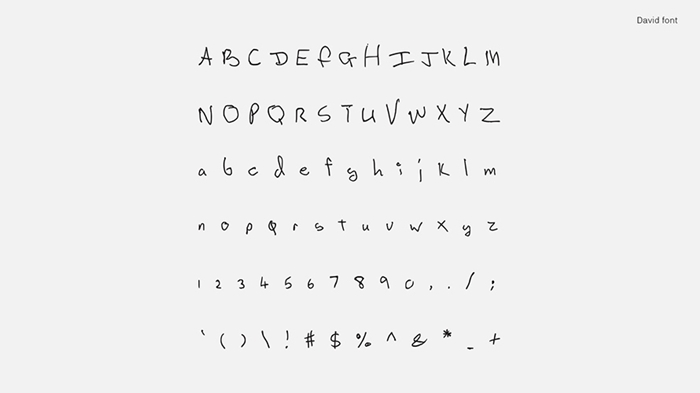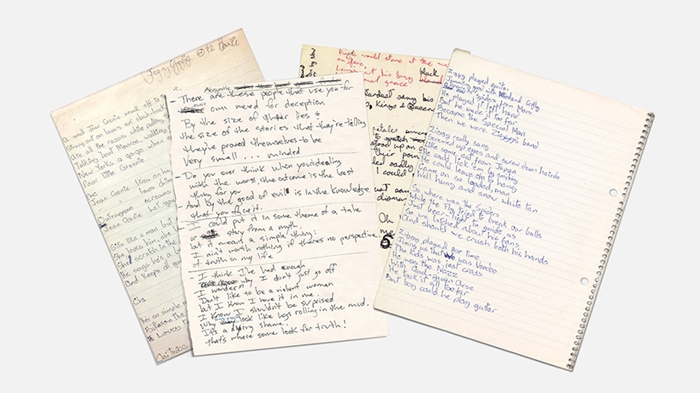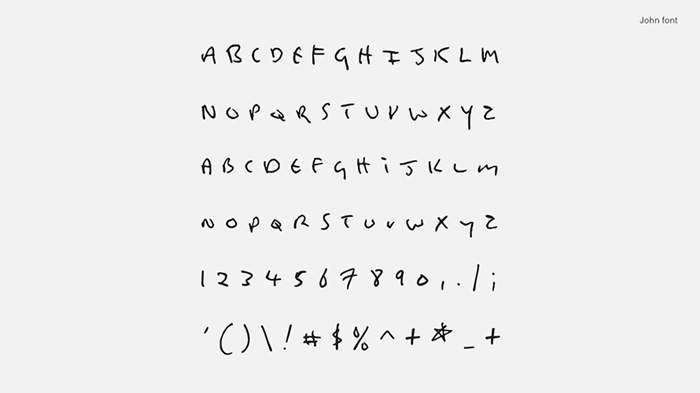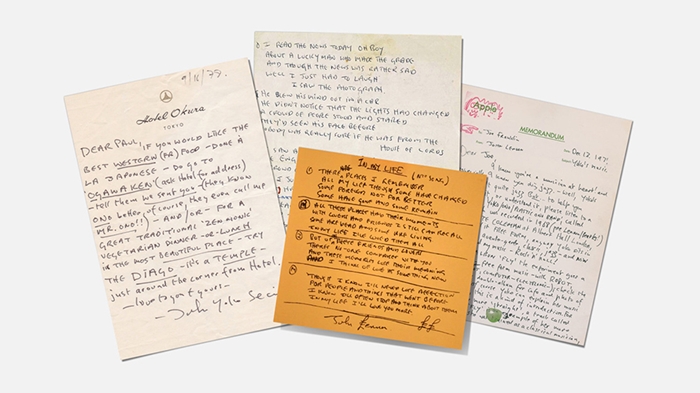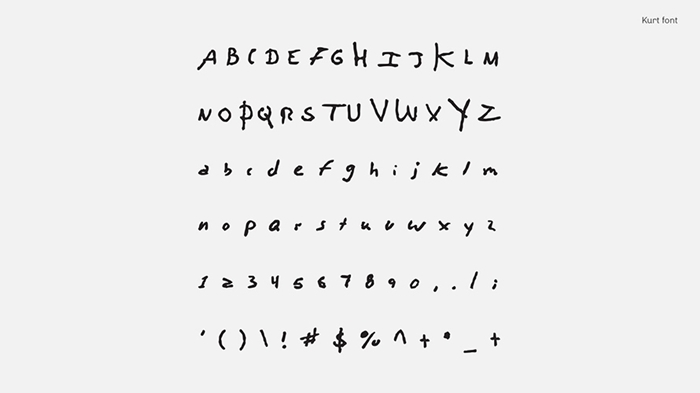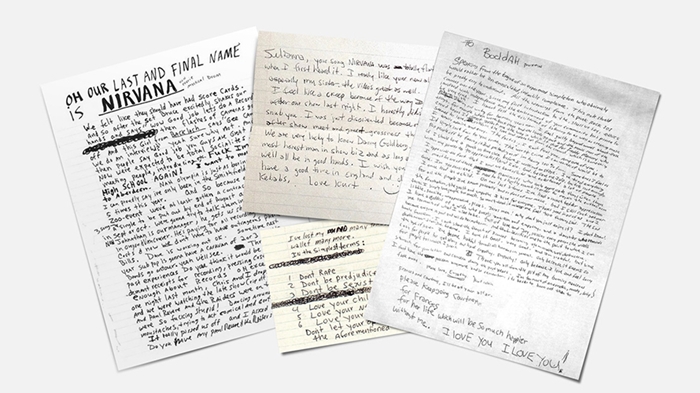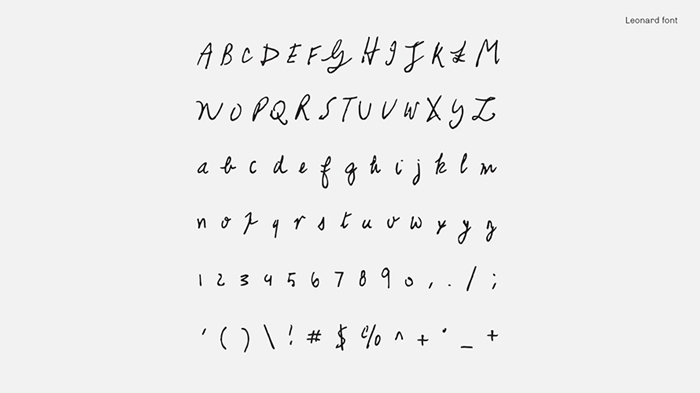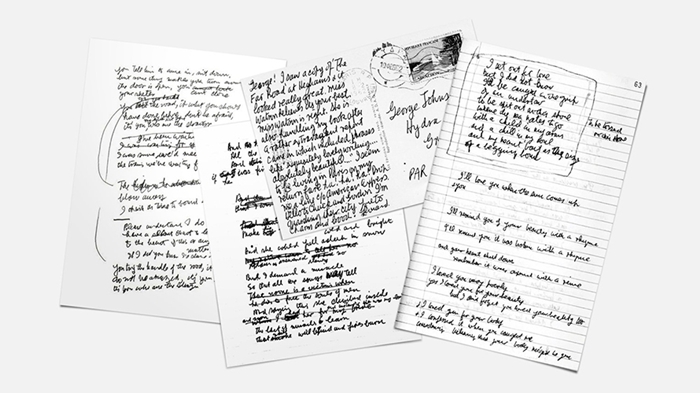
ชวนดู ฟอนต์ที่ออกแบบจากลายมือของเหล่า ‘ศิลปินผู้ยิ่งใหญ่’
ศิลปินหลาย ๆ คนนั้น แม้จะลาโลกไปแล้วแต่ผลงานและตัวตนของพวกเขานั้นยังคงสร้างอิทธิพลให้กับโลกอยู่ วันนี้ Marketing Oops จะชวนท่านผู้อ่านมาดู ‘ฟอนต์ลายมือ’ ที่สร้างขึ้นมาโดยได้รับแรงบันดาลใจจากลายมือของเหล่าศิลปินนักแต่งเพลงผู้ยิ่งใหญ่ที่ล่วงลับไปแล้วอย่าง Kurt Cobain, John Lennon, David Bowie, Leonard Cohain และ Serge Gainsbourg
Kurt Cobain
John Lennon
David Bowie
Leonard Cohain
Serge Gainsbourg
นี่เป็นผลงานของสองครีเอทีฟชาวฝรั่งเศส Nicolas Damiens(Design Director) และ Julien Sens (Creative Director) ที่ออกแบบฟอนต์ทั้งหลายเหล่านี้โดยมีจุดประสงค์เพื่อสร้างแรงบันดาลใจให้กับเหล่านักดนตรีในการแต่งหรือประพันธ์บทเพลงขึ้นมา